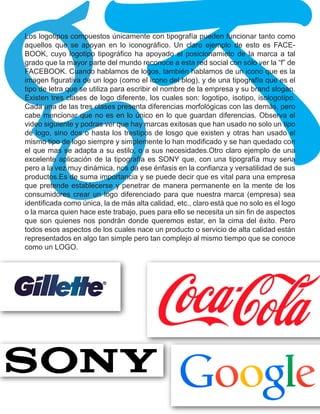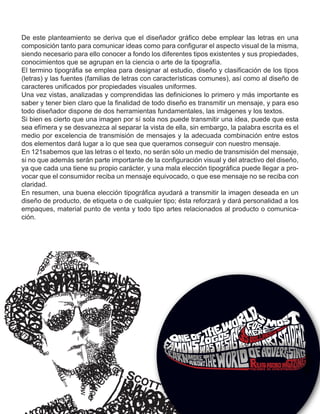
La
Uso Logos Función
La importancia que tiene la tipografía dentro de un diseño es tal que, con
sólo cambiar el tipo de fuente podemos dar otro contexto al mensaje que
queramos presentar, o una sensación o significado diferente.
En el manejo de la tipografía, debemos estar conscientes de que ésta es
tan importante como las imágenes mismas. Y que, tanto imágenes inapro-
piadas como fuentes tipográficas escogidas sin congruencia, pueden dis-
torsionar el mensaje que se busca transmitir.
En el caso particular del diseño de logotipos, la fuente tipográfica cobra su
máxima relevancia, ya que adquiere la resoponsabilidad de transmitir los
valores y todo aquello que la empresa o marca representa.
Helvética, Calibri, Franklin Gothic, Arial, Georgia, Gill Sans, Impact y una
infinidad de tipografías conforman un abanico de opciones del cual hemos
de echar mano de forma responsable para la creación de logotipos y mate-
riales de diseño.
Toda composición gráfica es transmitir un mensaje concreto. Para ello, el
diseñador se vale de dos herramientas principales: las imágenes y los
textos.
Las imágenes aportan un aspecto visual muy importante a toda composi-
ción. Estos con capaces de transmitir por sí solos un mensaje de forma
adecuada..
Sin embargo, el medio de transmisión de ideas por excelencia es la pala-
bra escrita. La esencia del buen diseño gráfico consiste en comunicar
ideas por medio de la palabra escrita, combinada a menudo con dibujos o
con fotografías. Además de su componente significativo, cada letra de una
palabra es por sí misma un elemento gráfico, que aporta riqueza y belleza
a la composición final..Es por esto, que el aspecto visual de cada una de
las letras que forman los textos de una composición gráfica es muy impor-
tante.
Los logotipos compuestos únicamente con tipografía pueden funcionar tanto como
aquellos que se apoyan en lo iconográfico. Un claro ejemplo de esto es FACE-
BOOK, cuyo logotipo tipográfico ha apoyado el posicionamieto de la marca a tal
grado que la mayor parte del mundo reconoce a esta red social con sólo ver la “f” de
FACEBOOK. Cuando hablamos de logos, también hablamos de un icono que es la
imagen figurativa de un logo (como el icono del blog), y de una tipografía que es el
tipo de letra que se utiliza para escribir el nombre de la empresa y su brand slogan.
Existen tres clases de logo diferente, los cuales son: logotipo, isologotipo.
Cada una de las tres clases presenta diferencias morfológicas con las demás, pero
cabe mencionar que no es en lo único en lo que guardan diferencias. Observa el
video siguiente y podras ver que hay marcas exitosas que han usado no solo un tipo
de logo, sino dos o hasta los trestipos de losgo que existen y otras han usado el
mismo tipo de logo siempre y simplemente lo han modificado y se han quedado con
el que mas se adapta a su estilo, o a sus necesidades.Otro claro ejemplo de una
excelente aplicación de la tipografía es SONY que, con una tipografía muy seria
pero a la vez muy dinámica, nos da ese énfasis en la confianza y versatilidad de sus
productos.Es de suma importancia y se puede decir que es vital para una empresa
que pretende establecerse y penetrar de manera permanente en la mente de los
consumidores crear un logo diferenciado para que nuestra marca (empresa) sea
identificada como única, la de más alta calidad, etc., claro está que no solo es el logo
o la marca quien hace este trabajo, pues para ello se necesita un sin fin de aspectos
que son quienes nos pondrán donde queremos estar, en la cima del éxito. Pero
todos esos aspectos de los cuales nace un producto o servicio de alta calidad están
representados en algo tan simple pero tan complejo al mismo tiempo que se conoce
como un LOGO.
De este planteamiento se deriva que el diseñador gráfico debe emplear las letras en una
composición tanto para comunicar ideas como para configurar el aspecto visual de la misma,
siendo necesario para ello conocer a fondo los diferentes tipos existentes y sus propiedades,
conocimientos que se agrupan en la ciencia o arte de la tipografía.
El termino tipográfia se emplea para designar al estudio, diseño y clasificación de los tipos
(letras) y las fuentes (familias de letras con características comunes), así como al diseño de
caracteres unificados por propiedades visuales uniformes.
Una vez vistas, analizadas y comprendidas las definiciones lo primero y más importante es
saber y tener bien claro que la finalidad de todo diseño es transmitir un mensaje, y para eso
todo diseñador dispone de dos herramientas fundamentales, las imágenes y los textos.
Si bien es cierto que una imagen por sí sola nos puede transmitir una idea, puede que esta